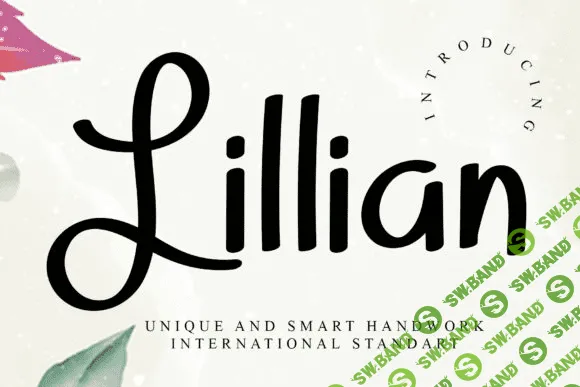
Название: Lillian Font
[Creativefabrica] Lillian Font
Лилиан воплощает в себе веселье, уникальность и подлинность.
Этот ослепительный шрифт дисплея превратит любую творческую идею в яркий образец!